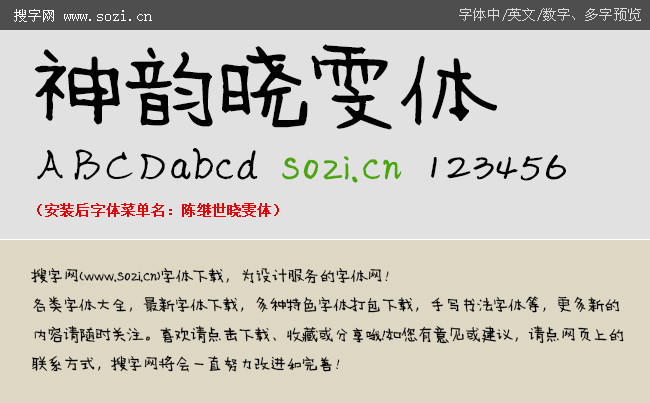
神韻曉雯體
搜字網(wǎng)給大家提供一款神韻曉雯體中文字體下載,神韻曉雯體字體是一款由神韻字庫(kù)設(shè)計(jì)師陳繼世打造的藝術(shù)字體,該字體將筆畫(huà)夸張,筆畫(huà)與筆畫(huà)采用非常規(guī)處理,結(jié)構(gòu)歪斜,重心不穩(wěn),使人產(chǎn)生青澀、萌動(dòng)的感覺(jué),能夠適用于藝術(shù)設(shè)計(jì)、包裝印刷、簽名設(shè)計(jì)、圖形設(shè)計(jì)等應(yīng)用。(本字體為個(gè)人非商用版,如需要商用請(qǐng)聯(lián)系作者購(gòu)買(mǎi)版權(quán))